Los Born Losers, la banda barcelonesa de instro-surf garage fuzz 60's, vuelve al ataque después de un par de años de sequía, al menos con esta banda, porque los componentes de la misma son conocidos por tocar en unos cuantos grupos al mismo tiempo.
Born Losers tienen una cierta obsesión con las pelis de bikers de los sesenta. De hecho, la banda nació en las largas conversaciones acerca de este género entre Pau y Dani sobre el mostrador del videoclub en el que trabajaba el primero, y toma su nombre de una de ellas. Gráficamente, estas películas son muy baratas y macarras, así que a la hora de afrontar el lettering que me encargaron para el cartel de su próximo concierto lo que me vino a la mente es una palo seco muy dura pero al mismo tiempo dinámica.
El logo al que llegué después de varias idas y venidas tiene el movimiento de las típicas letras surferas pero sin el buen rollo de éstas. Recordad que los Born Losers no hacen necesariamente música sobre el sol de California, sino más bien sobre un tipo que se acerca en una bobber y te mete un cadenazo en la cabeza.
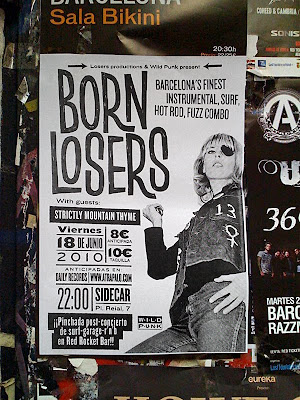
La aplicación en el cartel es muy sencilla: foto de rubia agresiva (prestada de The Hellcats y sugerencia de la banda) a la derecha, y logo e información práctica a la izquierda, todo con una palo seco (en este caso tipográfica). Blanco y negro muy contrastado en parte para seguir con la estética dura, pero también por una cuestión tecnológica. Os dejo una foto del cartel in the wild.